Using Creative Fabrica Fonts & Dingbats in Cricut Projects
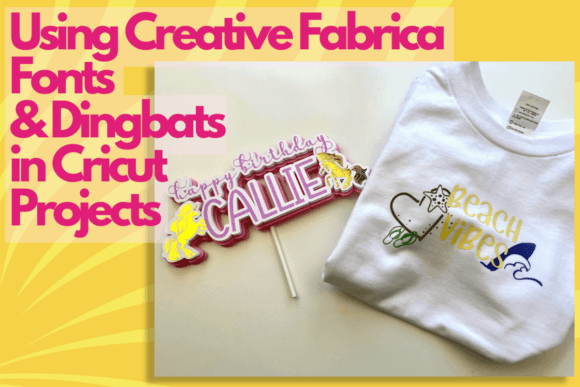
Việc tìm kiếm các thành phần thiết kế phù hợp có thể là một thách thức, nhưng Using Creative Fabrica Fonts & Dingbats in Cricut Projects cung cấp một bộ sưu tập đặc biệt giúp nâng tầm công việc của bạn ngay lập tức.
Được chế tác với độ chính xác cao, Using Creative Fabrica Fonts & Dingbats in Cricut Projects cung cấp các vector sạch, kiểu chữ mượt mà và giấy phép thương mại để bạn yên tâm.